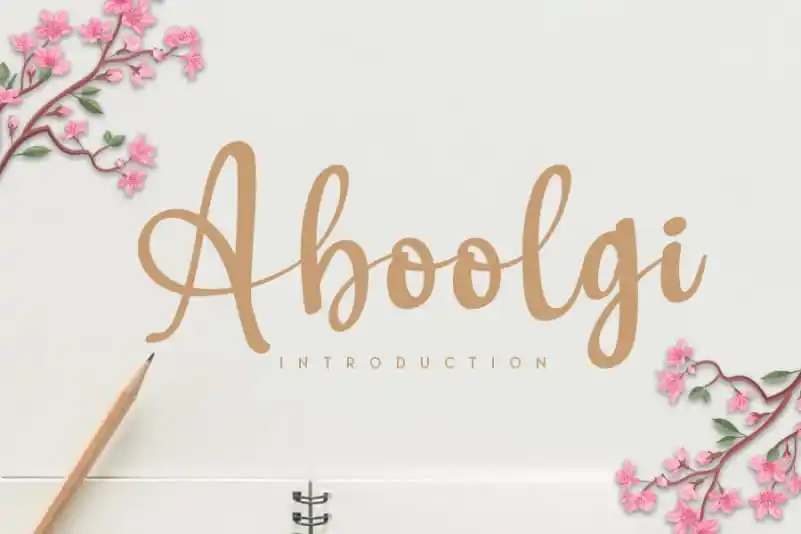
Aboolgi Handwritten Font – Download Grátis
A Aboolgi Handwritten Font é uma elegante caneta escrita à mão que descreve um estilo fluido, perfeito para seus projetos favoritos. Seu diferencial está na sua identidade única e estética atraente, certamente irá encantar designers de todos os níveis com seu design inovador e sofisticado. Sua elegância é tão vívida que pode tornar até mesmo os mais simples designs em obras de arte perfeitas. Para quem busca algo despojado e criativo na fonte à mão, a Aboolgi Handwritten Font é um projeto imperdível.